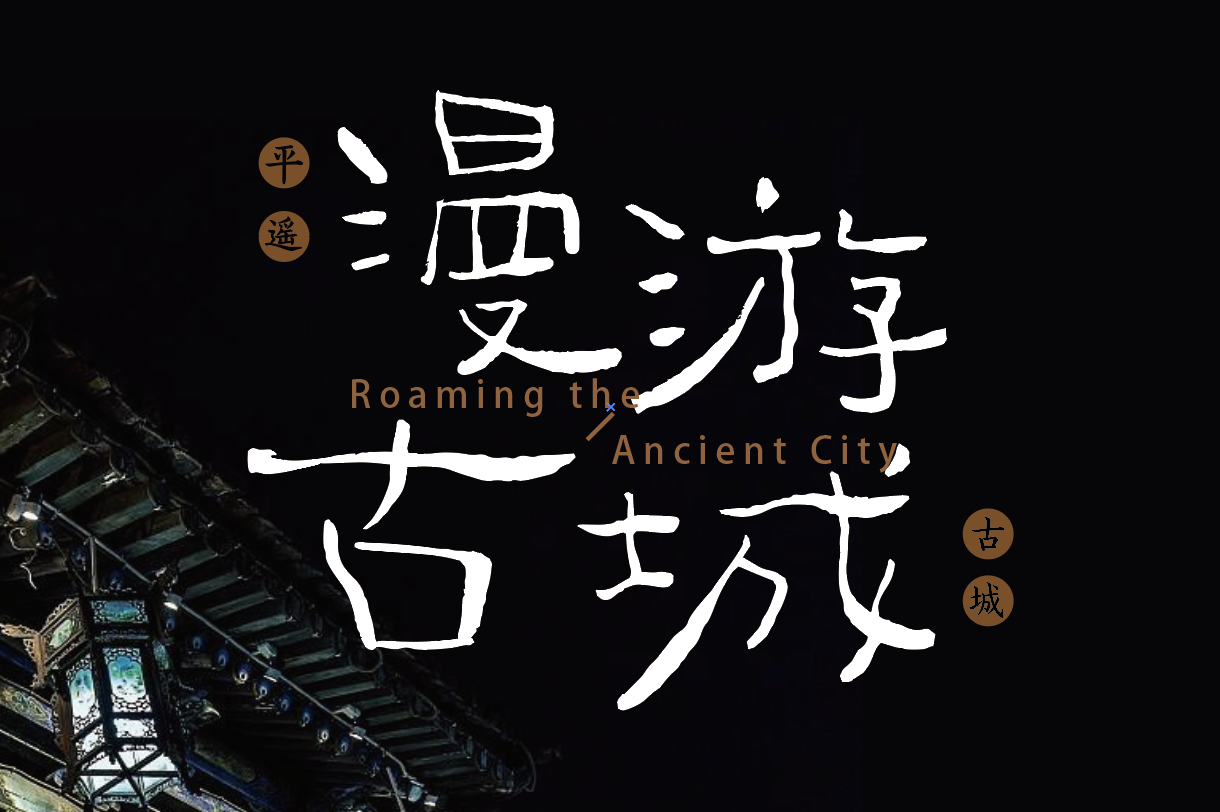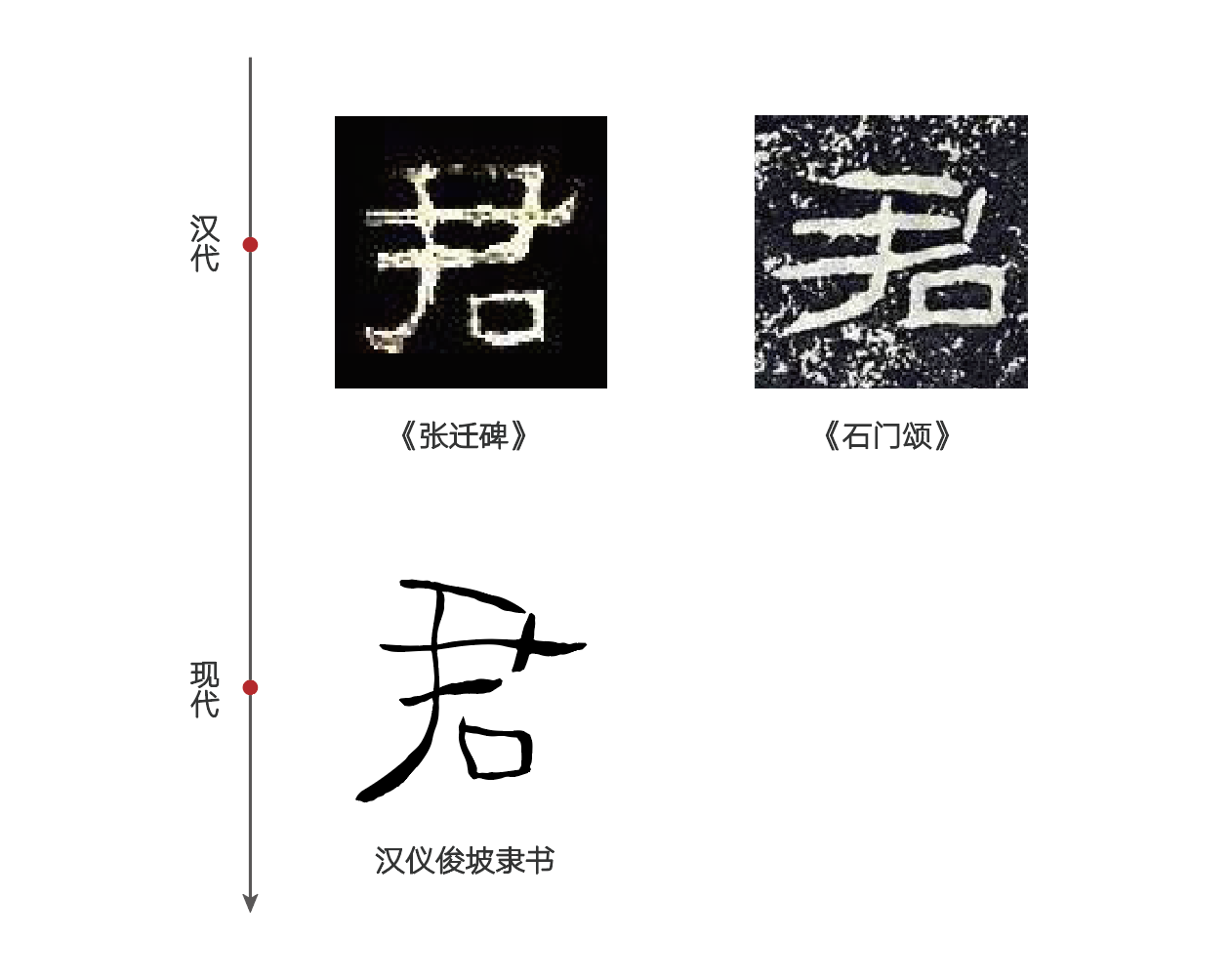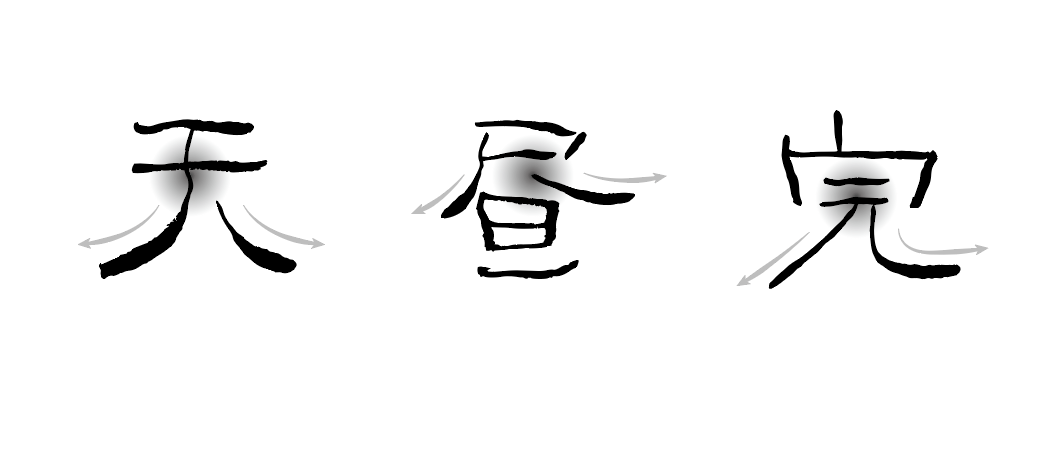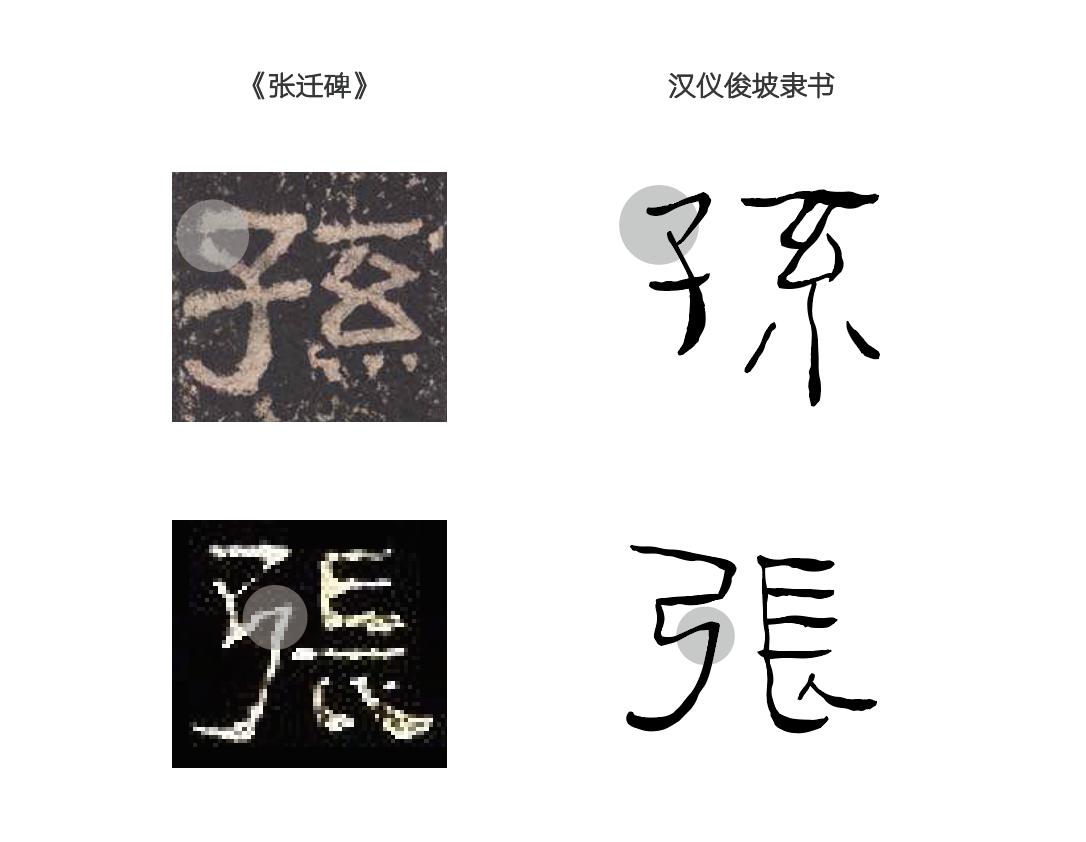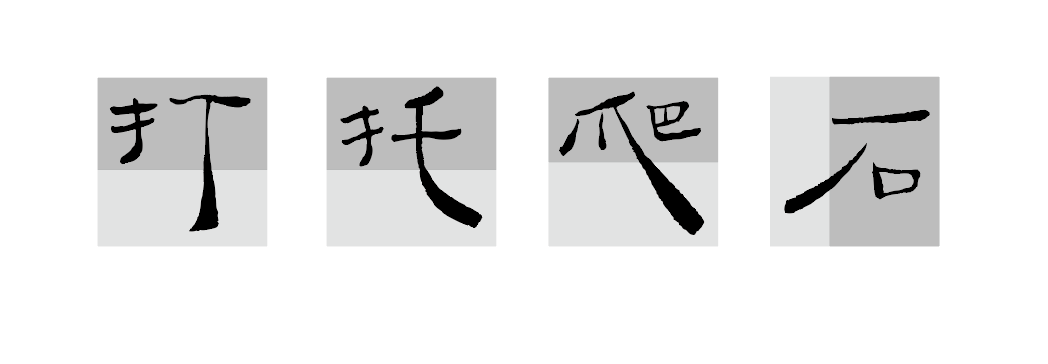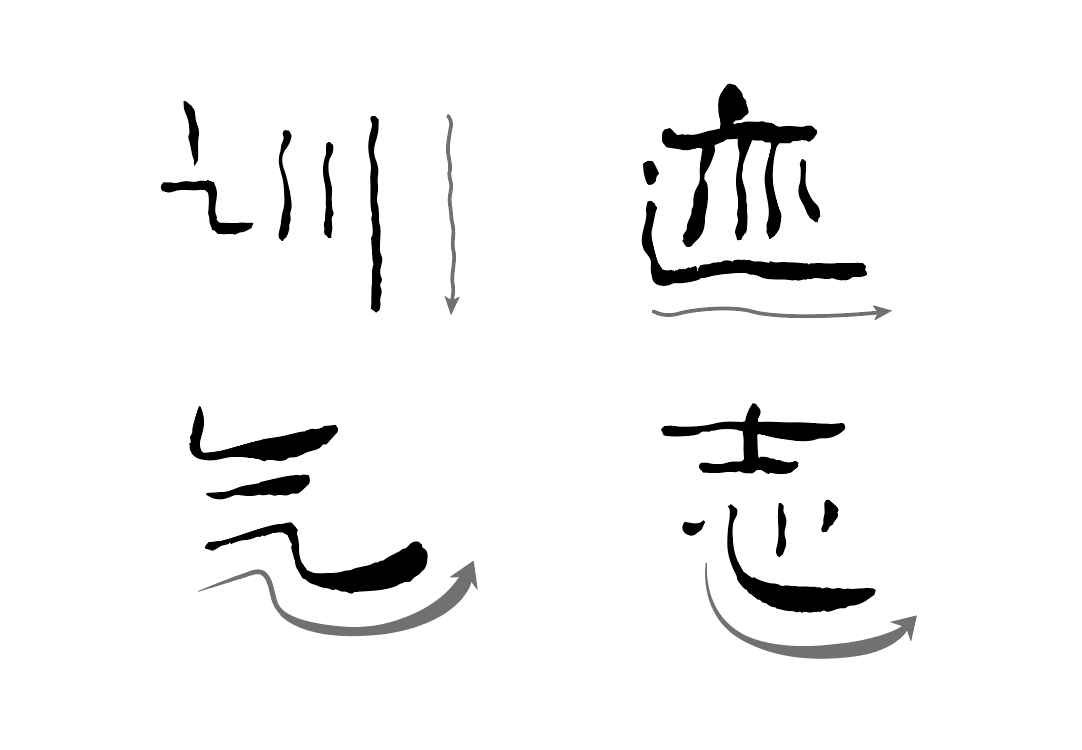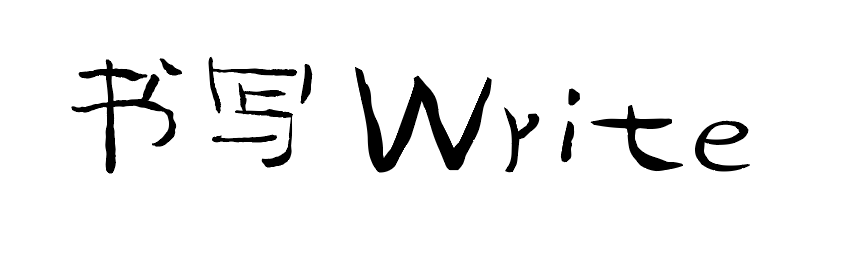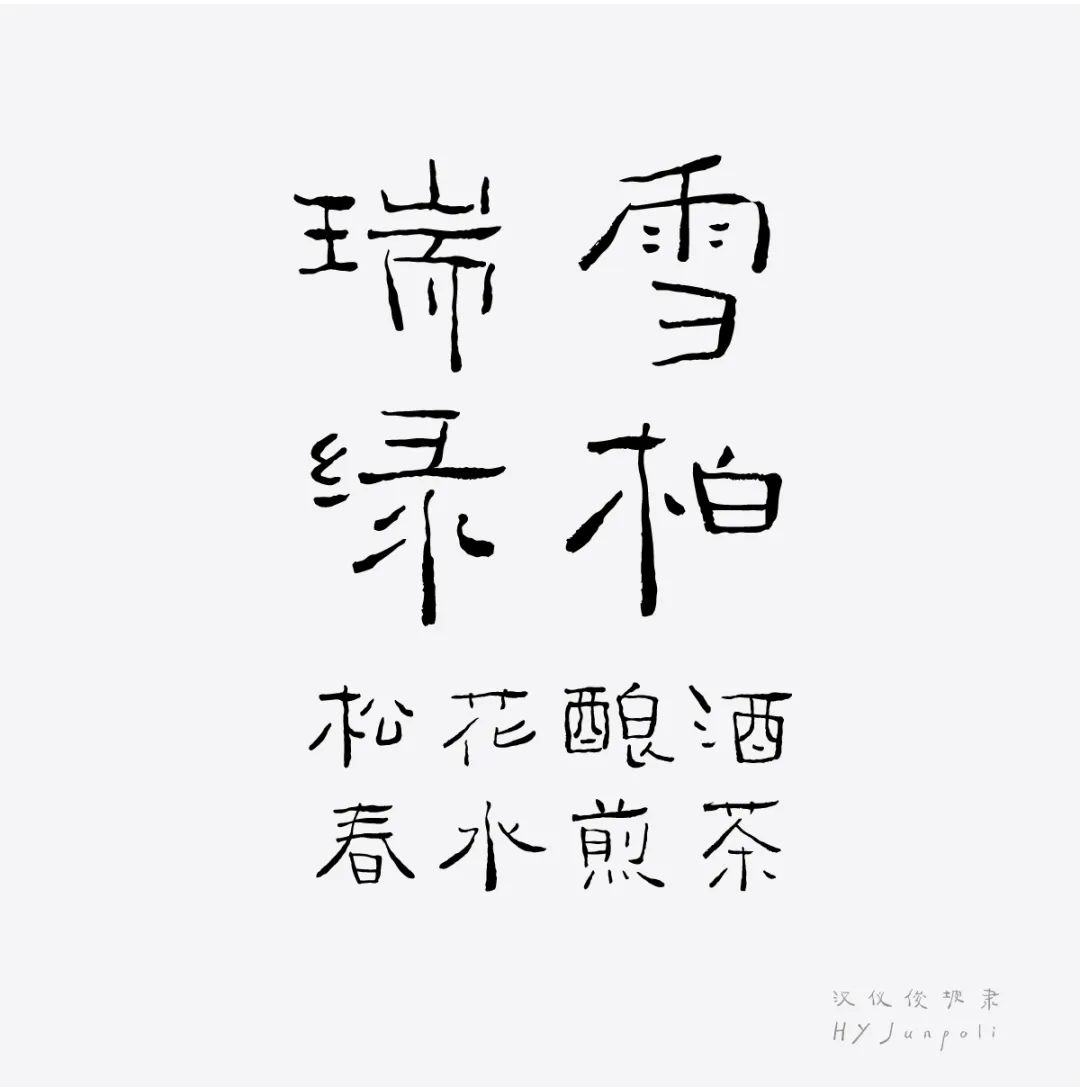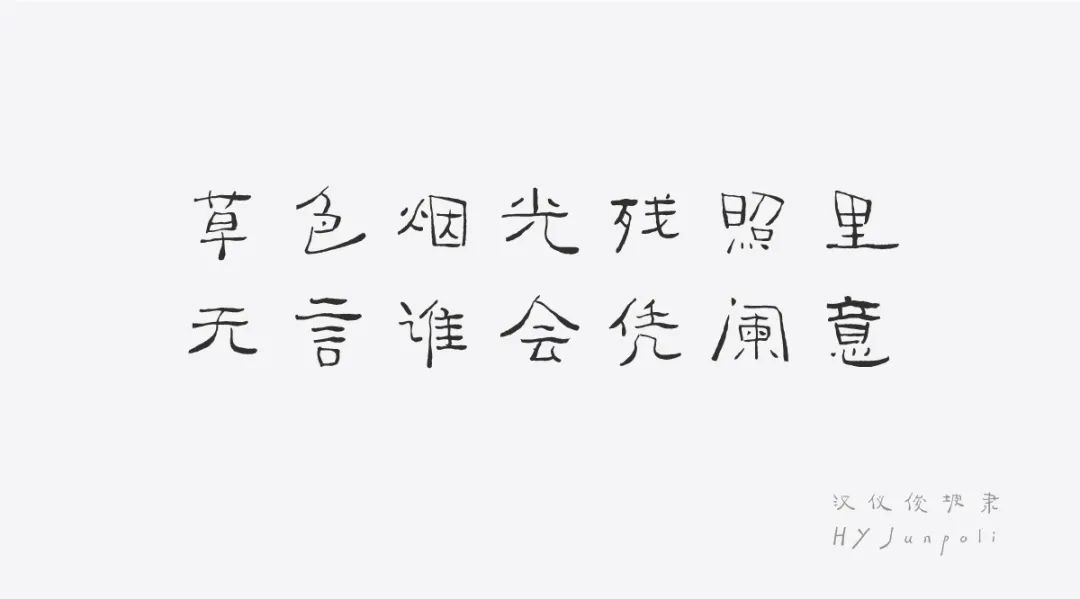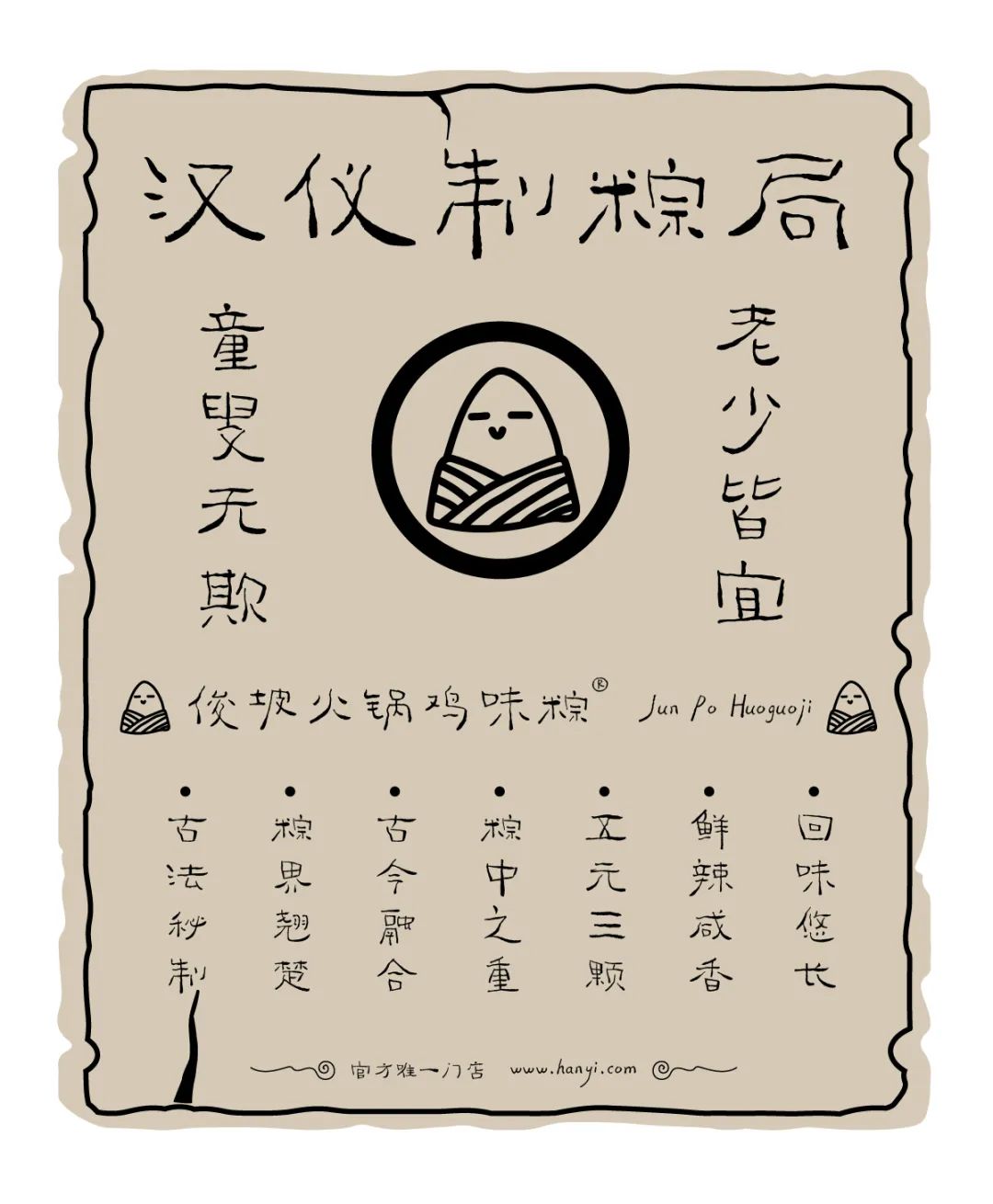
汉仪俊坡隶字体介绍,一款带有浓郁古拙意味的隶书作品
汉仪俊坡隶书 | 字形特点
“汉仪俊坡隶书”是一款带有浓郁古拙意味的隶书作品。它是由著名的简牍书法家刘俊坡倾力书写创作而成。“汉仪俊坡隶书”的诞生,不仅重新唤醒了简牍背后的民族记忆,更阐释传承一个民族的光荣与梦想。
“汉仪俊坡隶书”以汉代《张迁碑》和《石门颂》结体为构字基础,形成书风端正朴茂、结体巧妙大方,既有汉代庙堂遗韵,又含现代汉字审美的浪漫气息。
“汉仪俊坡隶书”以简牍墨迹的蝌蚪法和玉箸法为书写造型元素,字体内敛外放,典雅自然,有着含蓄蕴藉的审美情趣。
“汉仪俊坡隶书”的写法参考和保留了《张迁碑》的处理方式,还原了字体简单淳朴的韵味。
汉仪俊坡隶书 | 笔画特点
“汉仪俊坡隶书”笔画拖长似飘带状,字体显得灵动飘逸,结构疏密对比明显。这样的处理方式,打破了字体在演变过程中的僵化与呆板,赋予字体以灵性。
“汉仪俊坡隶书”笔画提按过渡明显,线条灵动活泼,粗细相间,赋予字体强烈的画面感,整体效果显得沉雄厚重。
汉仪俊坡隶书 | 中西文匹配
“汉仪俊坡隶书”西文字母充分吸收了中文结构,笔画和线条的特点,形成了带有古拙韵味的字母。中、西文搭配使用时呈现出更佳的视觉效果。
“汉仪俊坡隶书”西文字母提取了中文字体笔画的部分处理方式。降低了字母下缘线的位置,拉长了笔画结构。
汉仪俊坡隶书 | 字体展示